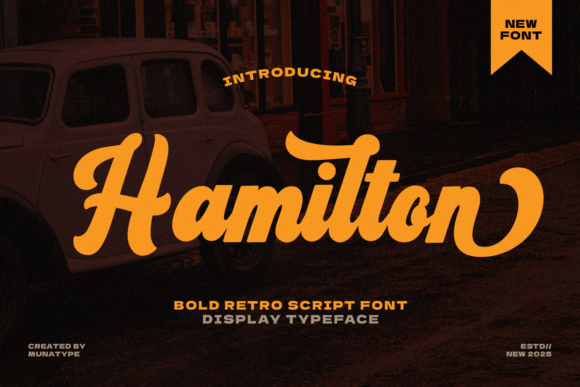
Hamilton
Het vinden van de juiste ontwerpelementen kan lastig zijn, maar Hamilton biedt een uitzonderlijke collectie die uw werk direct naar een hoger niveau tilt.
Of u nu POD-producten (Print on Demand), huwelijksuitnodigingen of afbeeldingen voor sociale media maakt, Hamilton is een ideale keuze.